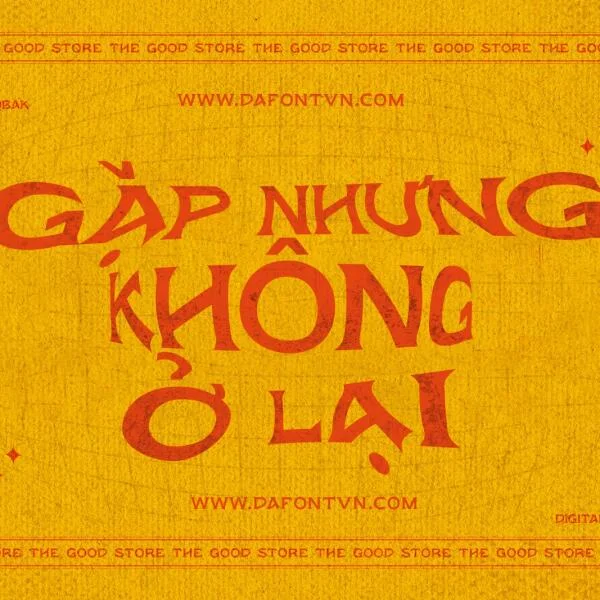
Download Font Daybreaker Việt Hóa - 1 chiếc font đẹp
Font Daybreaker là một font chữ đẹp với thiết kế được sáng tạo bởi Objets Dart. Tải về miễn phí ở cuối bài viết!
Tổng quan về Font Daybreaker
Font Việt Hóa Daybreaker - là một font chữ rất đẹp, khá phù hợp cho những thiết kế cổ truyền mang hơi hướng dân tộc và văn hóa truyền thống hoặc bất kỳ thiết kế nào khác. Font được việt hóa đầy đủ bởi LNTH và được tối ưu lại.